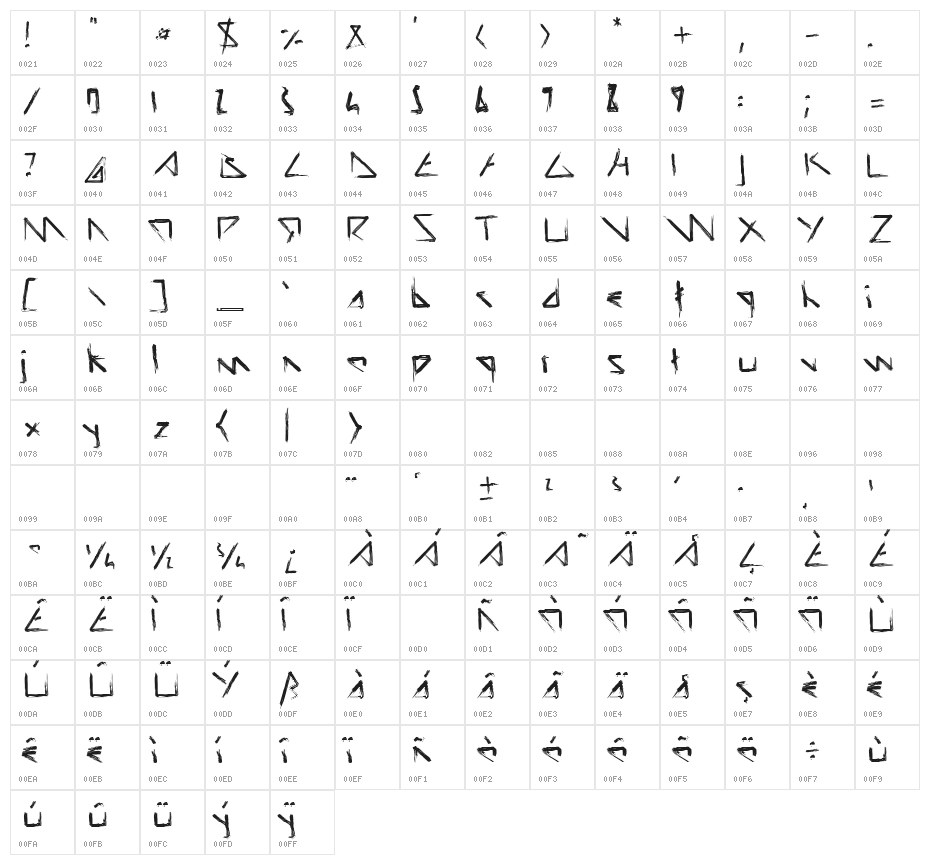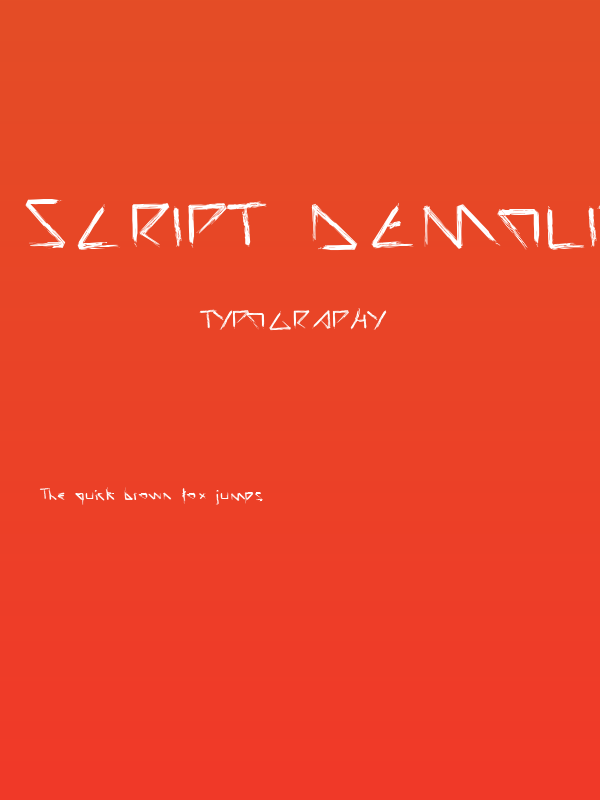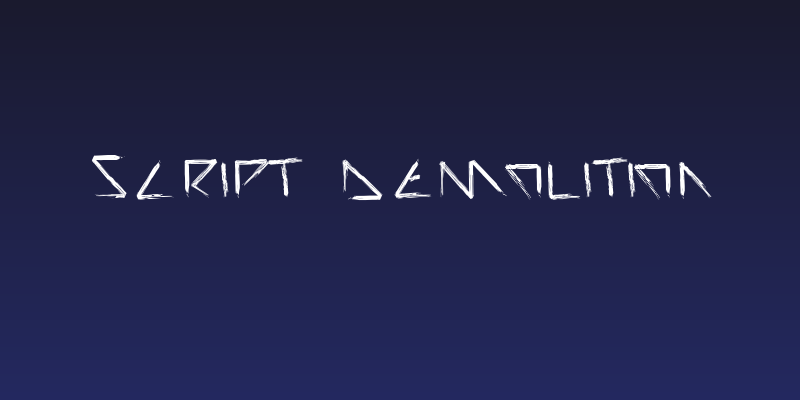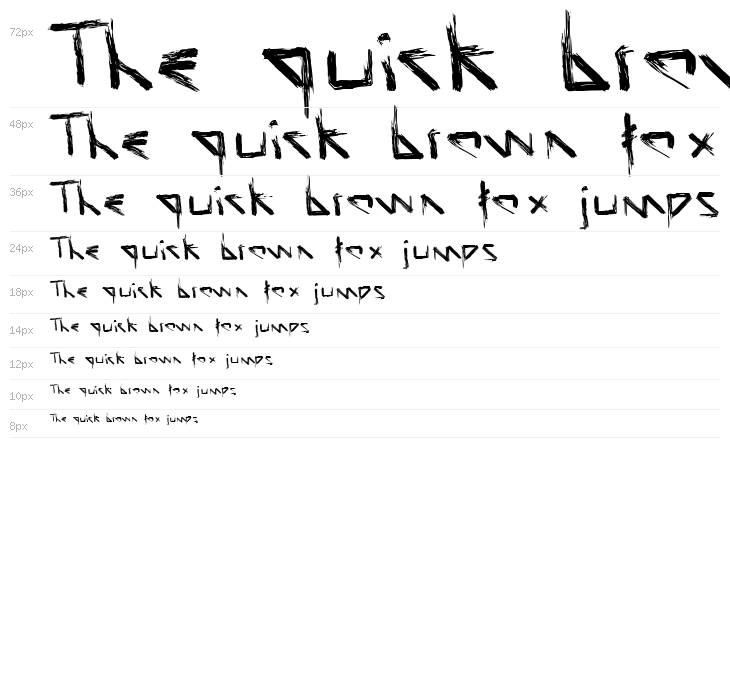
Script Demolition Font
| Gesamtstil | Grunge, Edgy, Distressed |
| Vorgeschlagene Projekte | Ideal for music album covers, movie posters, graffiti art, or any project needing a bold, rebellious aesthetic. |